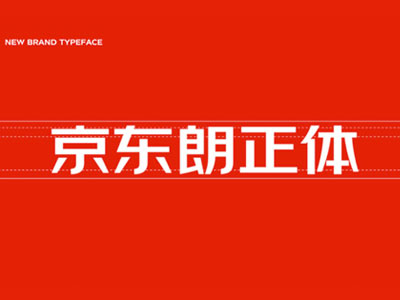
京东首款品牌定制字体!「京东朗正体」设计过程全纪录
京东推出品牌字体的原因
Type defines type. 在英文中,单词 Type 包含两个含义,文字和类型。这从某个角度说明了字体对于品牌的意义。一种字体能影响甚至决定人们对于这个品牌风格的认知。随着产品使用场景的不断拓宽,一个品牌的呈现已经不再局限于一个 LOGO 那么简单。
品牌可以通过 LOGO、品牌色、IP 形象、字体等多种方式与受众构建联系。根据权威机构 Salesforce 今年 4 月的调查,75% 的消费者期望在与品牌互动时获得一种持续性的、连贯的体验。
纵观京东现在的品牌光谱,可以发现,之前我们在字体方面的确是处于缺位的状态。而字体作为一个分布广泛的媒介,必将成为连通全部潜在品牌触点的重要工具。
因此,京东朗正体的推出,将会与我们现有的资源一起,全面提升京东的品牌体验的连贯性,并有利于构建新的品牌生态。
神秘组织,自给自足的艰难探索
京东朗正体其实脱胎于京东内部设计团队所称的「京东字体」。与很多品牌(IBM、奥美)相似,我们的品牌字体也是从我们的 LOGO 文字中延伸而来。
一开始,我们也是边学边做,通过已有的一些基础字体设计知识,从 LOGO 里寥寥无几的笔画中总结了一些笔画规律,比如横细、竖粗、点平、锐折等,然后将其应用到各个部门提过来的做字需求中。另外有时候也需要对其他部门提交的文字 LOGO 进行审核。
△ 这个神秘组织就是我本人
但是渐渐的,我们开始感到力不从心。一方面是随着京东业务不断扩充,希望设计京东字体作为 LOGO 的需求越来越多。使用京东字体作为标志,具有强品牌背书的优点,而且相比专门设计一个图形 LOGO 乃至一套 VI 体系,使用京东字体更加节省时间,具备更高的推广效益。但仅靠一个设计师来对接整个集团众多部门的做字需求,还是有点不堪重负。
△ 源源不断的做字需求
另一方面是我们意识到,我们根据 LOGO 字体制定的造字规则,其实非常模糊且局限,这也是我们缺乏字库设计的经验造成的。而这样的漏洞使得我们在实际的应用中遇到了问题。比如一开始我们简单地将撇的收笔都规定为纵切,但是在某些字中,使用横切收笔,视觉上却显得更为舒适。
后来我们在与专业的字体设计师沟通后了解到,这其实是因为在汉字中,单是一个撇笔就分为左上撇,斜撇,弯撇,直撇这么多种类型,而简单地将一个规则应用到所有的撇笔中,会造成某些字结构上的失衡。
交棒方正,专业化产出
就在京东字体的造字工程陷入困局时,市场部刚好找到我们,提出了与专业字库公司合作定制京东品牌字体的计划,从而推进品牌升级。我们与市场部一拍即合,确定了与方正的合作。于是,整个字库的创作主力转到了方正身上,而我们主要承担掌舵的角色,整个字库的制作也开始向专业化、规模化、系统化发展,生产速度更是呈现出爆炸性增长。
首先,我们与方正的老师确定了字体整体的基调,希望仍然保持简洁、直接、力量的感觉。对已有材料进行分析后,方正团队重新调整了字体的笔画、字面、重心和结构等方面,特别是对笔画粗细比例和规则进行了规范化。
可以看到,新版字体的纵横笔画比例从 20:11 缩小到 3:2 后,字面布白变得更均匀,辨识度也显著提高。
同时,方正团队对笔画规则的重新分类,也解决了我们之前碰到的难题。例如规定:点、撇、捺及镜像点撇的收笔采用横切,较为扁平的撇捺和镜像撇捺的收笔则采用纵切。
明确规则后,方正团队先小规模试点,做了 130 个字,这些字涵盖了京东常用字以及中文里的主要偏旁部首和部分独特字形。同时,方正也邀请我们为这些字提供意见。
由此,我们开始了字体找茬大赛。我们把这些字放大,打印后贴在墙上细细端详。近看,远看,坐着看,站着看,跪着看,走着看,调动起我们体内最原始的设计直觉,试图找出这些字里不自然的地方,然后贴上便利贴标记。后来我们甚至走火入魔,看字不是字。
△ 看字看到失智的同事
跷跷板两边——专业意见与业务需求
这次的项目合作,方正团队派出了两位重量级的设计专家,方正字库的设计总监仇寅老师与设计副总监汪文老师。(如此深厚沉淀的字体设计资历让我们忍不住就直呼老师)
一开始,我们还担心在项目过程中会比较被动,无法很好地参与到字型设计的讨论中。毕竟相比之下,我们简直是字体小白,缺乏系统的字体设计知识与建设大型字库的经验。但在合作的过程中,我们慢慢能体会到,从某个角度来说设计还是相通的。
在一期和二期字样中,我们都根据「设计直觉」,对一些基本结构提了调整意见,甚至直接上手做了修改的尝试,因为感觉这样讨论起来也比较直观。这也的确得到了方正老师们的认可与呼应,其中还包括一些比较重要的偏旁部首。
比如竖心旁、火字旁的两点,老师们一开始都做得特别纤细。这可能是因为点笔在初始的调性设定上,就被规定从起笔到收笔都不能有弧度。老师们或许是出于字面留白的考虑做小了。但我们认为从总体来看,还是显得过于「可爱」了点,于是将它们适当加粗,并向中心靠拢。老师也采纳了我们的意见,终稿效果呈现上双方都比较满意。
确认核心字样后,方正开始进一步快速地扩充字库。整个字库制作的时间虽然只有短短的 3 个月,但还是进行得比较流畅和有序的。
而这当中,还有一个无法忽略的角色,那就是市场部。市场部作为整个集团的品牌资源中继站,长期负责承接各个部门的设计需求,对字体在业务前线的实际应用效果有很强的发言权。于是,方正和市场部,自然落在了跷跷板的两边,而我们站在中间,既要信任双方,又要平衡好双方的意见,推进字库快速而高质量地产出。
这次制作间隙,刚好碰上了新板块业务——「京东健康」的品牌发布,因此方正团队需要临时先制作这几个字的标准字。在康字上,我们费了不少的功夫。
市场部认为方正给到的「康」字设计,有种不稳固的感觉。这可能是康字右下角的捺笔过高过短造成的。这可以理解,因为涉及到京东健康的业务范围和希望传达的品牌调性,业务方自然希望在字体标志上体现出稳定、安全的感觉。
但业务方提过来的建议,从设计上看还有欠缺,与其他字体也不成体系。因此我们在此基础上为方正老师提供了一些修改方向的建议,也就是让折捺更贴近地面,左边的两点也相应做出调整适应。
方正侧根据我们的意见,又做了进一步的创新修改。我们以设计角度和业务需求结合的角度进行挑选,认为将右边的点和捺打散,捺笔能获得更大的舒展空间,整个字符也「站得更稳」,选定了方案C。这个小插曲也就顺利解决了。
谁的字体?我们的字体
品牌定制字体,从名字上可以看出,似乎具有天然的专属性,它只属于其服务的品牌。但正如蒙纳在 2020 字体设计趋势报告所说,品牌的字体策略不应该是固定的、死板的,它更像是一个可扩展、可变化的工具,帮助我们实时重塑品牌。这意味着京东朗正体在未来仍将持续进化,更加开放。它不只是属于京东的字体,它还是我们所有人的字体,它试图满足设计师、合作商家、消费者等多方的需求。
京东朗正体目前仅有一个字重,比较粗,主要适用在大型标题或标志中,还不能满足目前众多文字内容样式的需要。后续我们将会制作更多字重,丰富京东朗正体的字体家族。我们也不排除京东朗正体会覆盖更多语言的计划。毕竟京东作为一个全球化的品牌,在各个国家的露出将会越来越多,使用字体在不同语境中保持品牌连贯性也一样至关重要。
除此之外,可变式字体(Variable Font) 可能是我们更长远的一个发展方向。可变式字体的特点在于其无限性,只需下载一套支持这种技术的字体,就可以直接调整字的各种外形参数,包括字重、字宽、衬线、斜度等。这既能减轻字体设计师的工作,也能为使用字体的设计师提供更多可能性。同时,这也有助于消除字体在各种电子终端演绎的屏障,释放更多品牌活力。目前我们正在与技术平台的小伙伴沟通这一计划的实现进程。
品牌战略公司 Lippincott 的负责人提到:「在这个新的时代,字体比任何时候,都更需要也更可能统一人们关于品牌的体验,并在各个渠道和载体上都实现无缝连接。」
这一次,我们做京东的品牌字体,当然不是为了「赶潮流」。它立足于现实环境的需要。京东,根源上看是一个提供零售基础设施服务的平台。这个服务,既是硬件上的,比如储存和传送包裹,也是软件上的,处理和分发信息。 而文字,作为信息的重要载体之一,是我们这一次尝试为京东创造设计价值而抓住的发力点和机会点。
和京东朗正体一起成长的历程,包含了我们在系统化字库设计中的懵懂探索,与跨界设计师合作的思想碰撞,乃至对京东品牌字体未来发展的想象,辛酸和快乐等比混合。
让我们期待京东朗正体的表现。